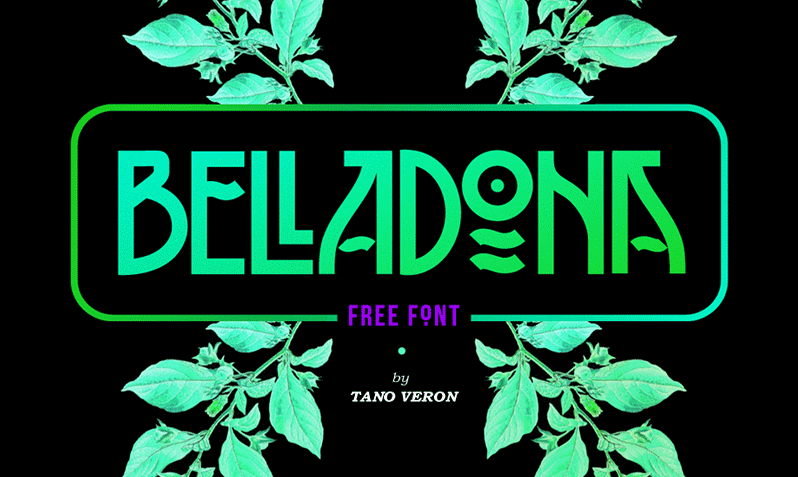
Belladona font – Download Grátis
A Belladona é uma elegante fonte display criada pelo designer Hamilton, perfeitamente adequada para uso pessoal ou comercial. Esta fonte oferece uma combinação única de elegância e modernidade, que faz dela uma escolha atraente para diversos projetos digitais. Específicamente projetada como uma fonte de display, Belladona destaca-se por sua disposição assertiva e força visual, tornando-a uma opção ideal para headlines e marcas. Suas formas delicadas contrastam com um aspecto forte, criando um contraste interessante que é extremamente atraente para gráficos e designers. Com esta fonte em seu arsenal de recursos, você pode explorar sua versatilidade tanto na criação de design digital quanto em elementos visuais impressos. As linhas equilibradas combinam com a disposição dinâmica da Belladona, resultando em uma combinação que certamente deixará seus projetos impressionantes. O uso desta fonte é suportado por seu designer, Hamilton, e pode ser usado de forma pessoal ou comercial. Experimentar o estilo moderno e elegante da Belladona pode transformar sua interface visual digital e presencial em algo único e atraente.